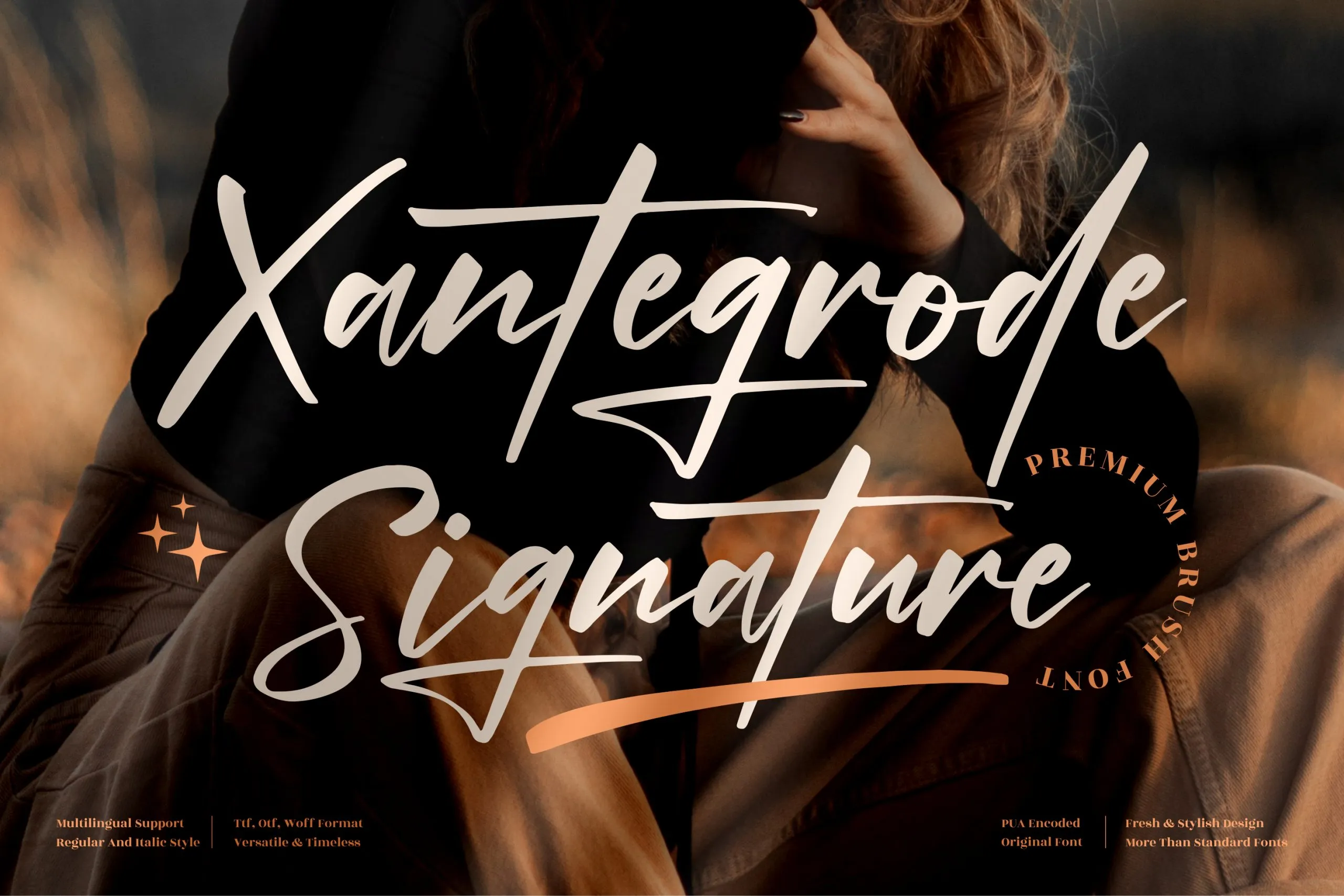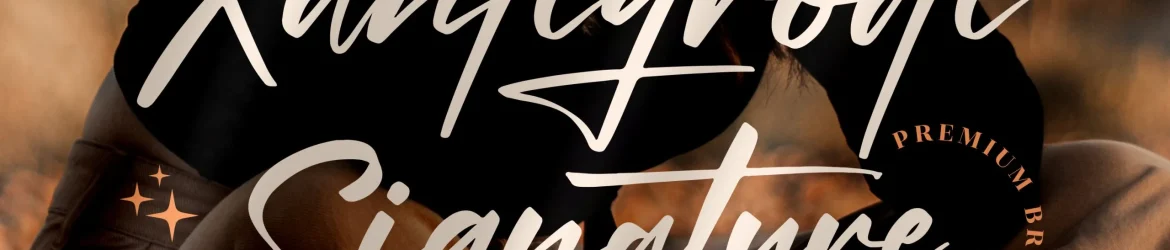
Xantegrode Signature Font é uma elegante fórmula moderna para chamativos textos que faz parte do catálogo impressionante de letras digitais da Perspectype Studio. Este belo conjunto de caracteres está projetado para dar um toque sofisticado a qualquer projeto, seja ele grande ou pequeno. Seja em logotipos e projetos de marca, designs de móveis, embalagens de produtos, talheres, carteirinhas, cartas de convidados, cartões de visitas, capas de livros, etiquetas de embalagem, até mesmo watermark para fotografias ou qualquer evento especial que precise de um toque luxuoso e personalizado. Xantegrode Signature Font é a escolha perfeita para aqueles desejando dar aos seus projetos um brilho premium e único, que se destaca em meio à multidão. Engane-se, ele não apenas oferece uma variedade de estilos, mas também uma experiência única na escrita de chamados modernas e criativas.